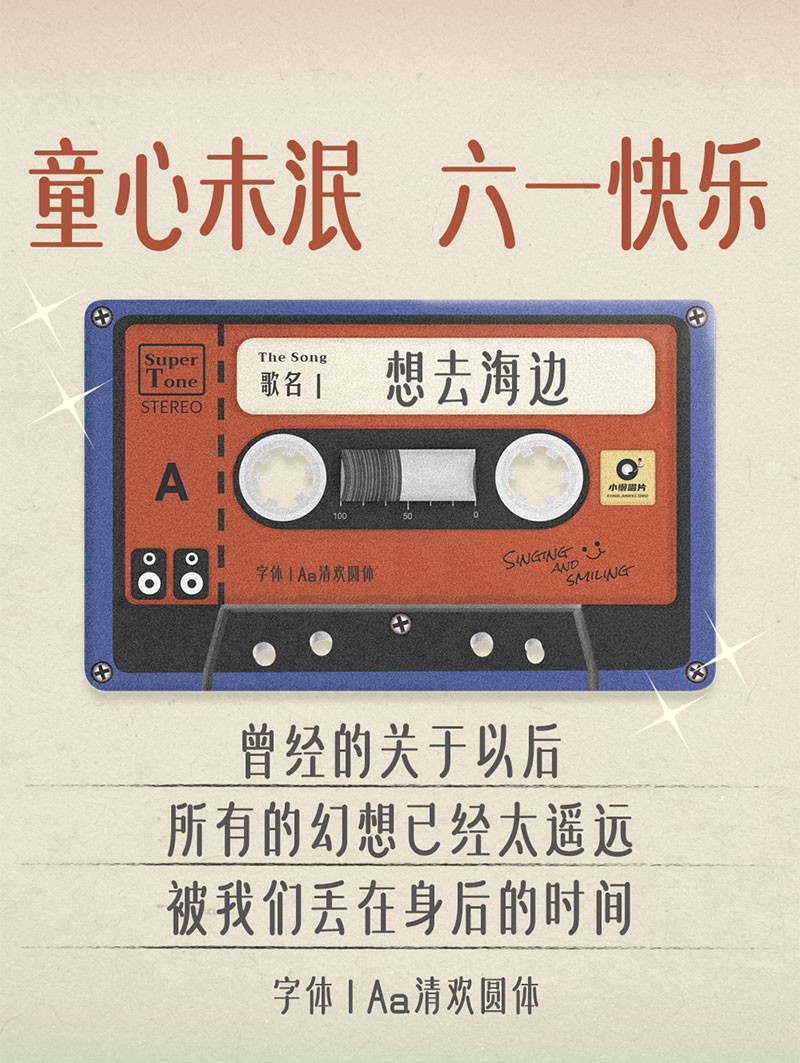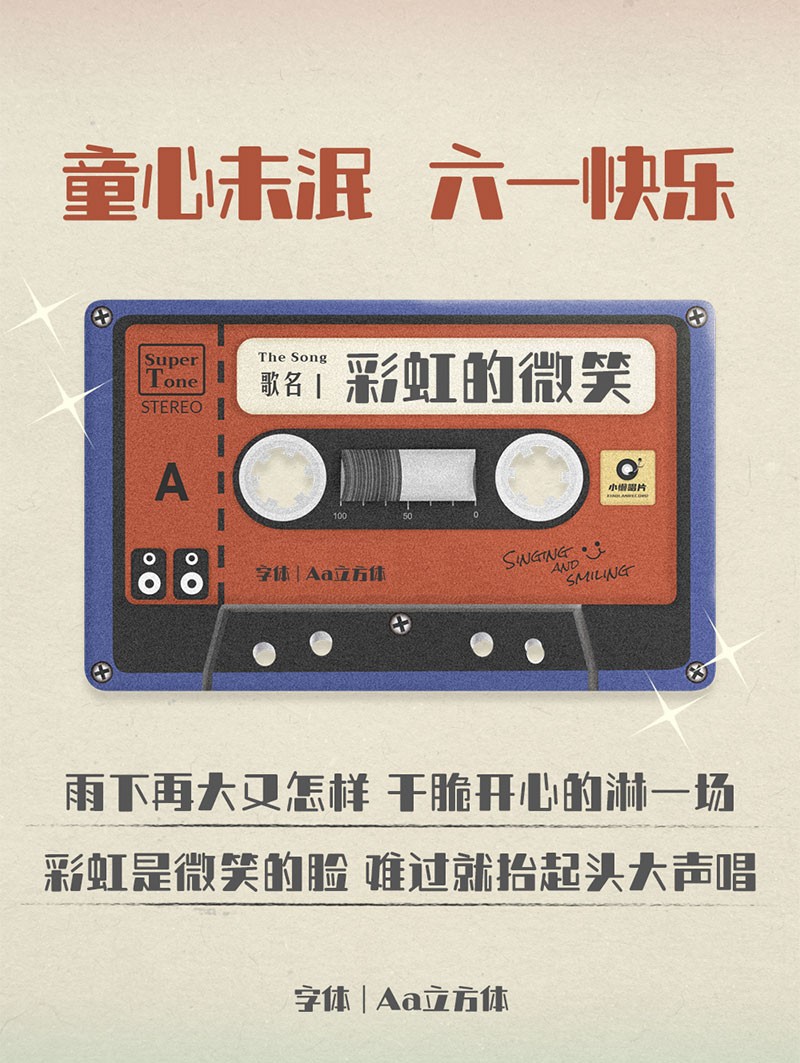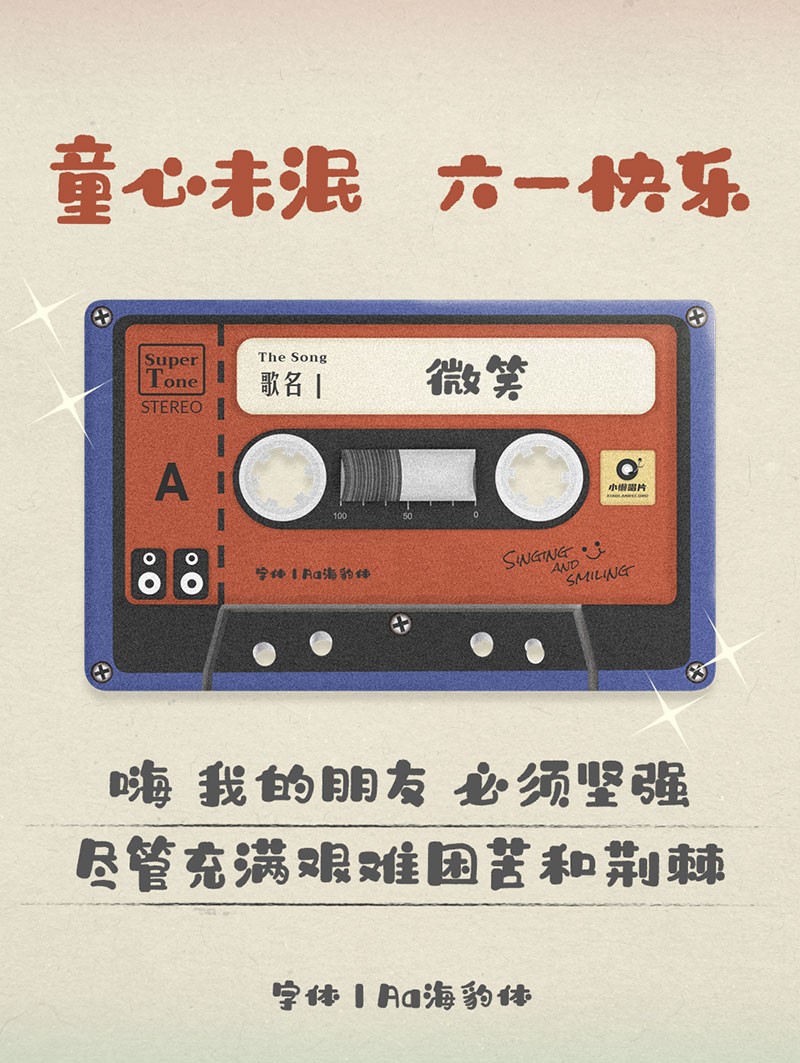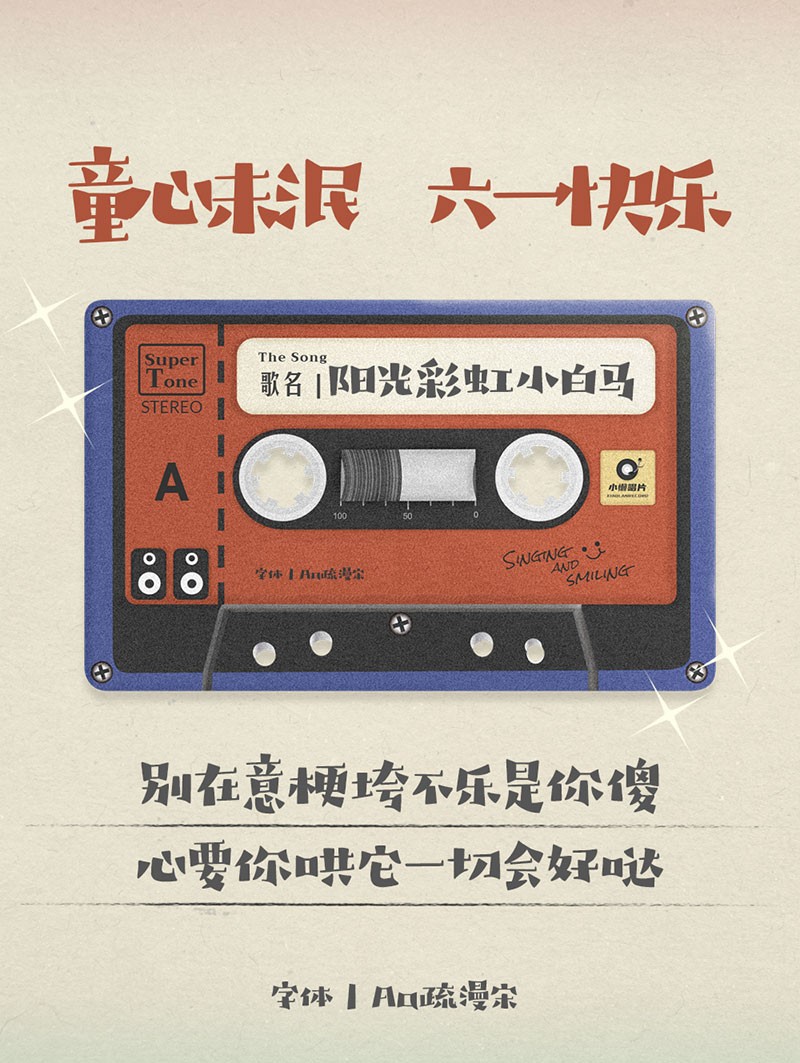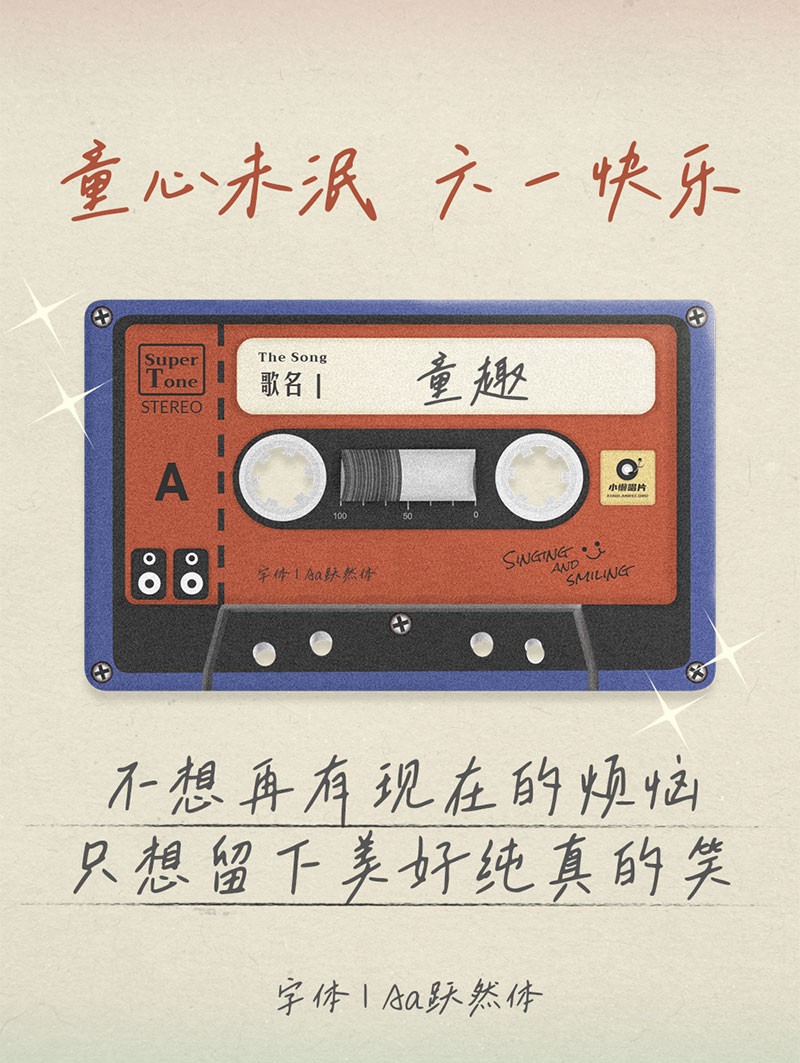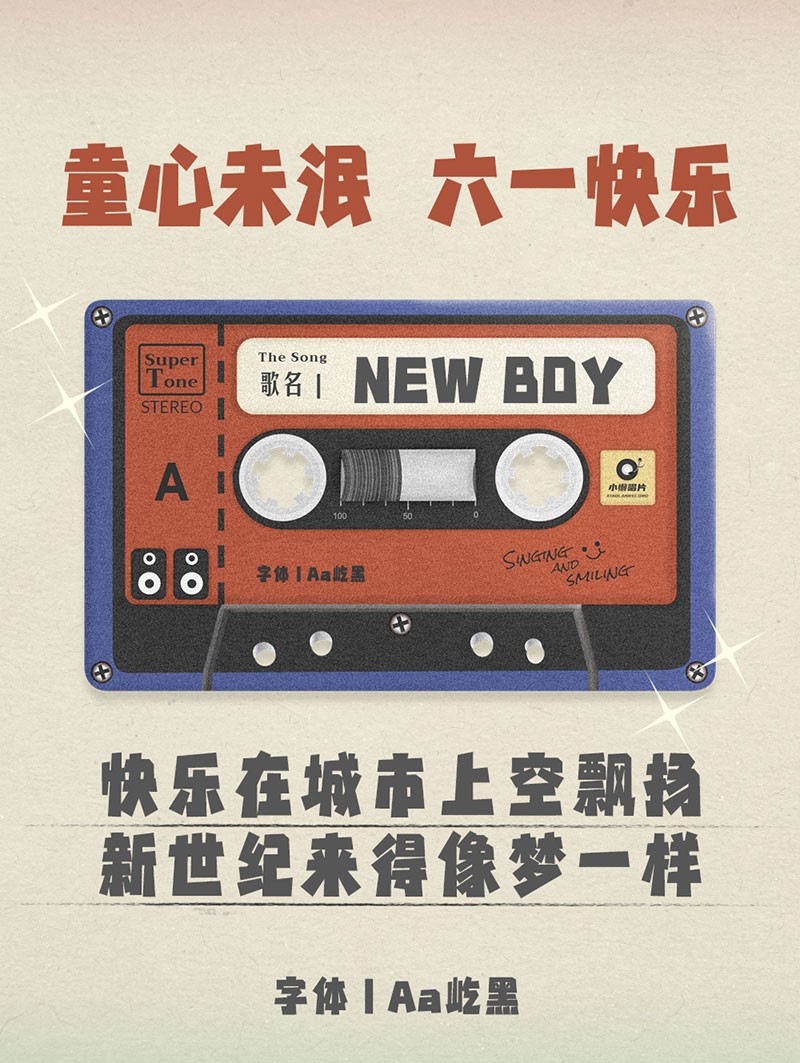
6款有趣的儿童节中文字体
Aa海豹体
笔画圆润Q弹,俏皮可爱,字形结构变化多样,粗细对比强烈,富有节奏感。你看它,像不像隔壁小朋友嘟嘟的小脸。
Aa疏漫宋
以手绘的形式给予字体活泼的风格,三角形与直线的交流,大小不一的字形结构,配合跳跃的结构,展现出不一样的宋体。就好似蹦蹦跳跳的小朋友,拥有天真浪漫的个性。
Aa立方体
将笔画的粗细对比极端化,再加上小圆角装饰,表现科技感的同时还有点笨拙可爱。
Aa屹黑
笔画结构极具块面感,整体重心略高,形成一款挺拔有力的创意黑体。
Aa跃然体
以狭小的中宫和拉长的放射型笔画让字体飘离大地翩翩起舞,整体向右倾斜统一感强且动势明显,特别适合表现旋律或旅途等线性推进的主题。
Aa清欢圆体
一款横细竖粗的标题圆体,拉长的字形和垂顺的竖笔画给字体带来优雅的视觉感受,粗竖笔画的圆头又平添一份优雅童趣的气质。